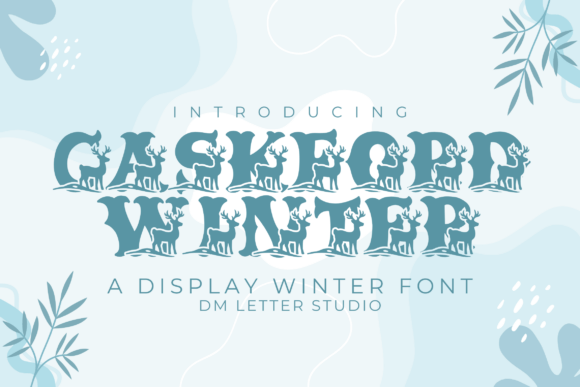
Caskford Winter
適切なデザイン要素を見つけるのは難しい場合がありますが、Caskford Winterは作品を即座に引き立てる優れたコレクションを提供します。
POD(オンデマンド印刷)製品、結婚式の招待状、またはソーシャルメディアのグラフィックを作成している場合でも、Caskford Winterは理想的です。